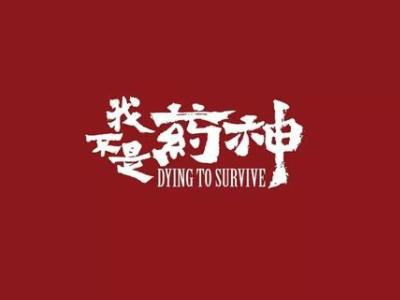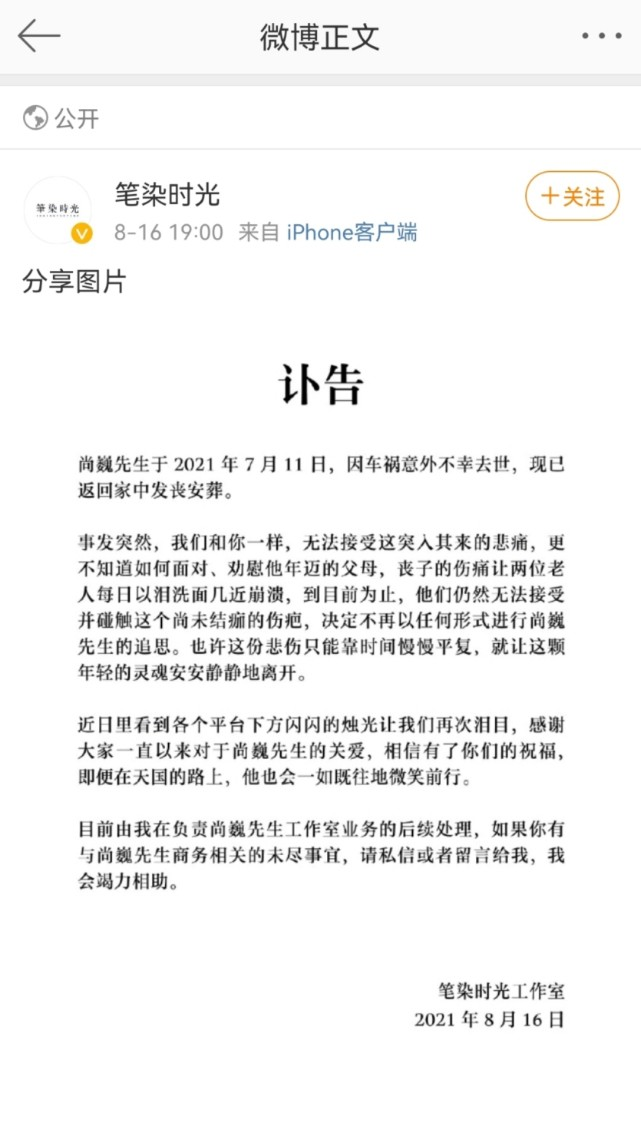
《我不是药神》字体设计师尚巍因车祸去世,年仅30岁
2021年8月16日,尚巍工作室官方微博笔染时光发布讣告,著名字体设计师尚魏于2021年7月11日发生车祸,于2021年8月16日不治去世,现已返回家中安葬。
笔染时光工作室讣告
尚巍是独立设计师,曾为《我不是药神》《悟空传》《白日焰火》《军师联盟》等影视作品片名及字幕进行字体创作。
老谋子的《影》,电影特辑中也是用的尚巍手书。
尤其不得不提的就是《我不是药神》,他为电影定制了片头片尾字幕手写字体,算是国内首部了。
尚巍曾写过《我不是药神》字体创作心得,称“字写得很素,安安静静地去表达吧”。